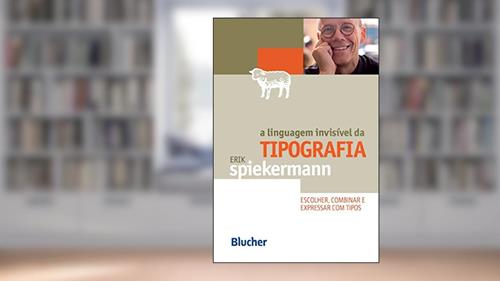
Resumo de A Linguagem Invisível da Tipografia: Escolher, Combinar e Expressar com Tipos, de Erik Spiekermann
A Linguagem Invisível da Tipografia: Escolher, Combinar e Expressar com Tipos, do autor Erik Spiekermann
Se você já se perdeu na imensidão das fontes tipográficas e não sabe se deve usar Arial ou Comic Sans (dica: fuja da Comic Sans!), então A Linguagem Invisível da Tipografia é o seu mapa do tesouro. O autor, Erik Spiekermann, um verdadeiro mago das letras, nos guia pela floresta densa da tipografia com a maestria de um chef que sabe exatamente como temperar uma salada - e o tempero, aqui, é a escolha das fontes.
Vamos lá, quando você pensa em tipografia, provavelmente imagina um punhado de letras jogadas na tela, certo? Mas, amigo, você está prestes a descobrir que as letras têm sentimentos e personalidades próprias! Spiekermann faz um trabalho primoroso em nos mostrar que cada tipo de letra não é apenas uma escolha estética, mas também uma escolha comunicativa. Uma fonte bem escolhida pode fazer sua mensagem brilhar como um diamante, enquanto uma escolha errada a enterra num buraco negro.
O livro é dividido em partes que exploram como escolher, como combinar e como expressar usando tipos. Sim, você leu certo! Escolher uma fonte é quase como escolher um parceiro para dançar: se não houver sintonia, a coisa tende a ficar estranha. Aqui, a combinação de tipos se torna um jogo, e nosso autor é o árbitro, explicando que, apesar do amor incondicional pelas combinações, algumas misturas são um crime contra a humanidade-ou no mínimo, um atentado à estética.
Um dos principais pontos que Spiekermann enfatiza é a importância da legibilidade. Você pode ter a letra mais estilosa do universo, mas se ninguém conseguir ler, qual é a vantagem? É como cantar lindamente e, ao mesmo tempo, ser desafinado. O autor apresenta vários exemplos práticos que vão desde o sublime até o escandaloso. E, por favor, não pense que ele vai deixar você na mão-há dicas arrasadoras que mostram como aplicar seus ensinamentos na vida real (sim, até mesmo no seu próximo projeto de trabalho).
Mais adiante, Spiekermann dá um giro pelos diferentes estilos tipográficos e suas histórias. Você vai descobrir que cada fonte tem uma biografia que faria inveja a muitos personagens de novela. Você sabia que algumas fontes foram projetadas para parecer mais "humanas"? Isso mesmo! Elas têm sentimentos também. Para não deixar você com a pulga atrás da orelha, vale ressaltar: não tem spoiler aqui porque estamos falando de letra e não de finais trágicos.
Vale lembrar que o livro também discute a psicologia das formas. Não, não estamos falando de psicologia no sentido de ficar deitado no divã, mas sim sobre como as formas das letras podem impactar a percepção do público. Uma fonte pode evocar seriedade, enquanto outra pode fazer você se sentir como se estivesse em uma festa infantil!
Se preparar para uma revolução tipográfica é a meta, então A Linguagem Invisível da Tipografia é o seu manual de instruções. Com a combinação de humor e informação, Spiekermann faz a leitura não só interessante, mas também respirável. Agora, se você não sair deste livro mais sábio e com uma lista de fontes preferidas, pode ter certeza de que o problema não é com o autor, mas com as suas escolhas!
E, para concluir, se você ainda não se convencemos de que a tipografia é mais do que apenas rabiscos, lembre-se de que uma boa tipografia pode transformar um simples "Oi" em um "Oi, estou aqui e quero ser lido!". Então, mãos à obra e bom aprendizado!